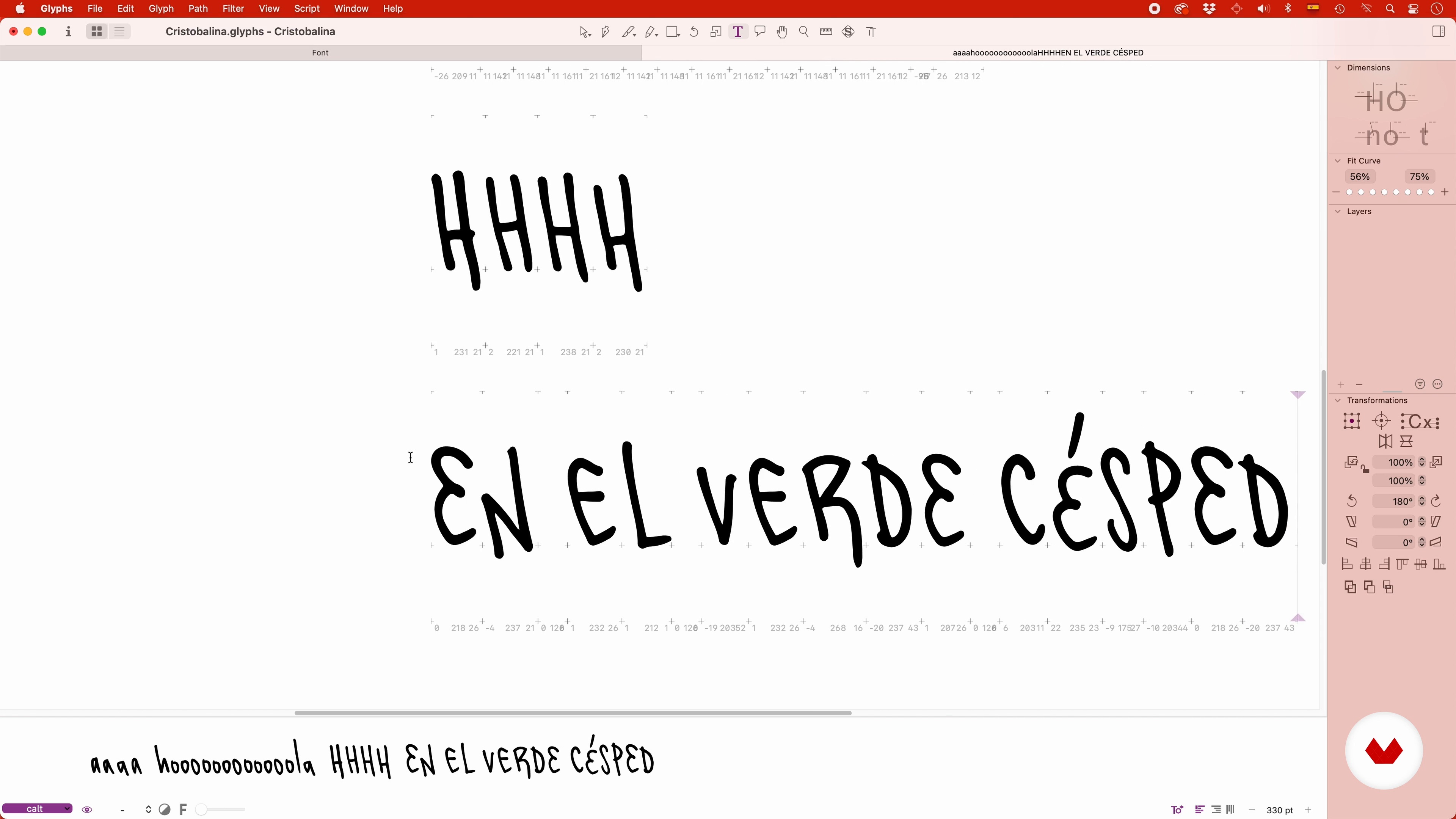
Fonte aleatória
“Por fim, vou lhe dizer como você pode fazer sua fonte parecer ainda mais manual. Para fazer isso, usarei a magia do OpenType e glifos alternativos.”
Nesta videoaula, Cristóbal Henestrosa aborda o tópico: Fonte aleatória,que faz parte do curso online da Domestika: Design de tipografia: digitalize sua letra. Transforme sua escrita à mão em uma tipografia digital única para dar personalidade a cada uma de suas obras.
“fonte aleatória Já que estamos fazendo uma fonte manual e o computador não é muito bom em ser manual, podemos enganá-la um pouco com a magia do OpenType e gerar glifos alternativos que são substituídos uns aos outros para dar a aparência que nossa fonte parece feita à mão. Agora vou explicar como. Olha, eu vou te dizer muito rapidamente. Gerei uma fonte chamada Cristobalina Alternates, que já inclui vários glifos alternativos para quase todos os caracteres da minha fonte. Todos os números têm três alternativas, também todas as letras maiúsculas, também todas as vítimas e também todos os dia...”